10 Font Coffee Shop yang Mendorong Pelanggan Masuk
Diterbitkan: 2023-01-24Tahukah Anda bahwa 50 persen pelanggan baru tertarik dengan papan nama ? Itu saja adalah alasan yang cukup untuk memberikan font kedai kopi dengan hati-hati jika Anda ingin usaha Anda berhasil.
Yup, menjalankan sebuah kafe membutuhkan lebih dari sekadar menyajikan sajian lezat dan minuman dingin. Di zaman sekarang ini, ketika minum kopi telah berkembang menjadi budaya tersendiri, kualitas minuman yang Anda sajikan sama pentingnya dengan cara Anda mengemas bisnis Anda – mulai dari interior dan musik hingga font dan logo kedai kopi.
Di sini, di Penji, misalnya, kami mendapat banyak permintaan desain grafis dari usaha kedai kopi yang meningkatkan permainan mereka di bidang pemasaran. Lagi pula, mereka tahu bahwa daya tarik visual sangat penting dalam membangun merek yang ingin didukung oleh pecinta kopi.
Jika Anda sedang mencari font kedai kopi untuk digunakan untuk bisnis Anda, jangan mencari lebih jauh karena kami telah mengumpulkan yang terbaik secara online.
1. Font Elit Khusus
Jika Anda mencari font pedesaan untuk kedai kopi Anda, lihat font ini dari Astigmatic One Eye Typographic Institute. Ini memberikan karakter tertentu tanpa berlebihan, seperti font mesin tik lainnya. Konon, font pada logo ini akan membuat kebersamaan terasa seperti tempat di mana Ernest Hemingway akan menikmati kafe noir.
2. Font ShoCard Caps NF
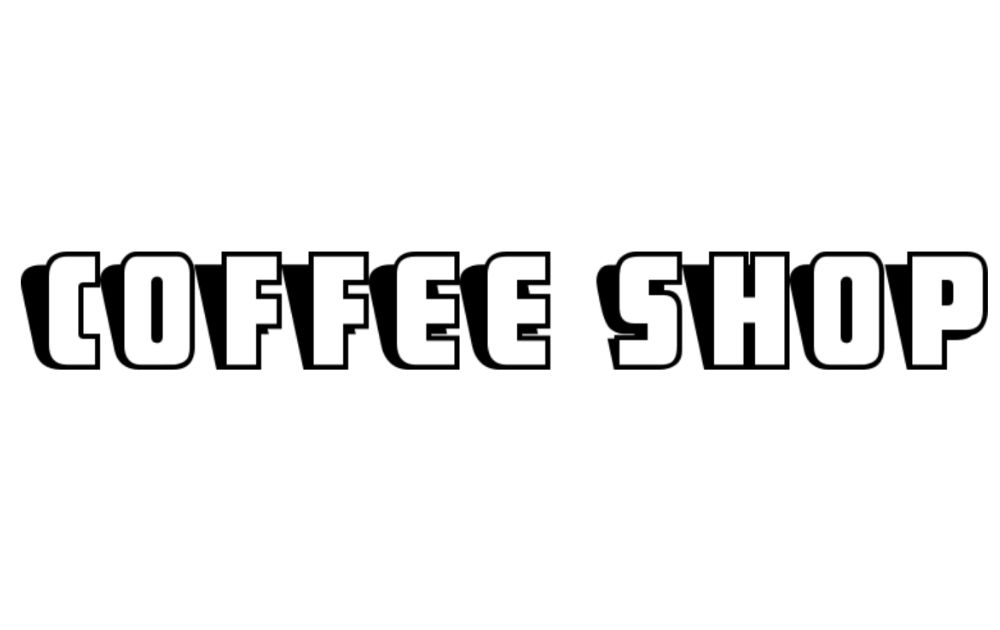
Font oleh Nick Curtis ini terlihat menyenangkan, retro, dan mengingatkan pada tahun 90-an. Bayangan hitam menciptakan kontras yang mencolok pada visual, sehingga menciptakan tampilan 3D. Menggunakan font ini pada aset branding Anda akan membuat usaha terlihat menarik dan jauh dari kafe biasa.
3. Huruf Rochester
Jika Anda mencari font kedai kopi yang terlihat elegan tanpa terlalu feminin, lihat opsi dari Font Diner ini. Sementara beberapa font skrip cenderung terlalu bergaya hingga terlihat berisik secara visual, yang satu ini terlihat cukup sederhana dengan bakat yang tepat.
4. Font Grenadier NF
Tidak semua font sans-serif terlihat kusam dan membosankan. Lihat saja font yang dibuat oleh Nick Curtis ini. Gaya art deco terlihat vintage dan glamor pada saat bersamaan. Yang mengatakan, itu akan menjadi font yang luar biasa untuk digunakan jika Anda mencoba menyalurkan getaran yang canggih namun ramping.
5. Font Alba Reguler
Inilah font sans-serif lain yang menarik perhatian! Gaya Font-a-licious ini adalah salah satu font kedai kopi yang membuat Anda berpikir tentang restoran. Dan seperti restoran retro favorit Anda, restoran ini terlihat mudah dan tidak rumit namun tetap nyaman dan familiar di saat yang bersamaan.
6. KG Summer Sunshine Reguler
Ini font bagus yang dibuat oleh Kimberly Geswein. Teks lucu itu terlihat seperti coretan dari buku catatan seseorang. Yang mengatakan, menggunakan font ini pada logo atau desain menu Anda pasti akan memberikan kafe Anda daya tarik yang menyenangkan. Dengan nada yang sama, ini mungkin cara yang baik untuk berhubungan dengan segmen audiens yang lebih muda.
7. Fredericka the Great Font
Inilah gaya gambar tangan lainnya oleh Font Diner. Jika Anda tertarik untuk menggunakan font espresso blue mountain yang populer di menu Anda, Fredericka the Great akan menjadi pilihan yang bagus untuk judul. Karena keduanya terlihat digambar dengan tangan, menu Anda akan terlihat dipesan lebih dahulu dan buatan tangan – seperti banyak pecinta kopi yang menyukai secangkir kopi mereka.
8. Font Piring BB
Font dari Blambot Comic Fonts ini tidak terlihat seperti apa pun yang Anda dapatkan dari pembuat font kopi. Sebenarnya, ini terlihat seperti ilustrasi manual yang mungkin dikerjakan oleh seorang seniman selama berjam-jam. Dan jika menyangkut visual pemasaran, itu selalu merupakan hal yang bagus!
9. Font Gisellano
Jika Anda mencari font yang memberikan kesan hangat dan nyaman, pertimbangkan karya yang dibuat oleh Yan Studio ini. Dari semua font yang berbeda untuk usaha kafe, gaya skrip melengkung seperti ini memberi kesan kafe ramah lingkungan. Kedai kopi dengan logo font ini terlihat seperti tempat Anda duduk dengan cappuccino dan cupcake sambil membaca buku yang bagus.
10. Font Homerun
Font dari madeDeduk ini adalah pilihan yang bagus jika Anda mencari font skrip yang tidak terlihat terlalu kaku. Jika Anda tertarik dengan font kaligrafi kopi seperti font skrip kafe, maka Anda pasti akan menghargai yang satu ini. Karena guratannya terlihat spontan, memberikan kesan barista menulis nama di etalase toko pagi-pagi sekali sebelum menyeduh teko segar.
Rendahnya
Berikut adalah beberapa petunjuk cepat yang perlu diingat saat memilih font merek:
- Jenis huruf harus dapat dibaca dan cukup jelas untuk dibaca.
- Ada banyak font cantik di luar sana, itu sudah pasti. Tetapi batasi font Anda menjadi dua hingga tiga per materi.
- Saat menggabungkan font, pastikan ada tingkat kontras . Misalnya, gabungkan font serif dengan sans serif.